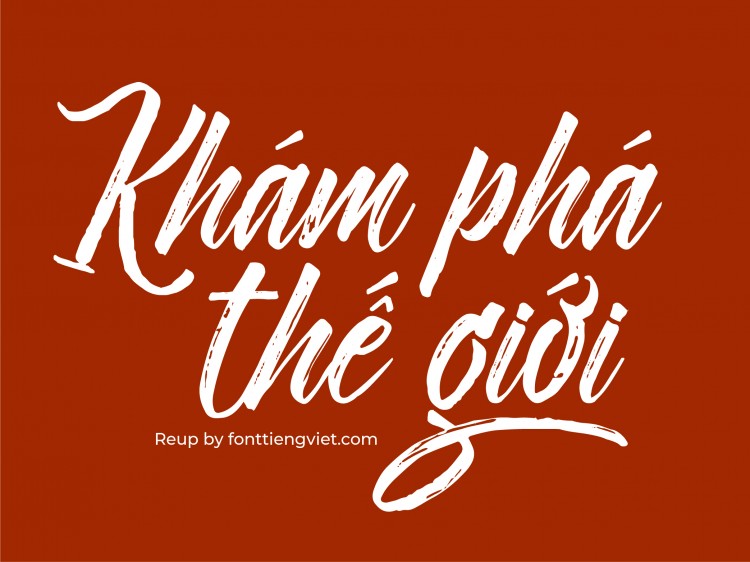
Font việt hóa FS Novitha Script
Tải Font việt hóa FS Novitha Script Miễn Phí Cho Thiết Kế Thư Pháp Hiện Đại
Giới thiệu về Font việt hóa FS Novitha Script
Trong thế giới đồ họa hiện đại, việc tìm kiếm một bộ Font Miễn Phí mang phong cách mềm mại nhưng vẫn giữ được sự chuyên nghiệp là điều rất quan trọng. Font việt hóa FS Novitha Script chính là giải pháp hoàn hảo cho các bạn học sinh và giáo viên khi muốn trang trí tài liệu học tập hoặc làm thiệp chúc mừng. Đây là kiểu chữ Script dạng viết tay đầy uyển chuyển, mang đậm nét nghệ thuật thư pháp đương đại. Khi được việt hóa chỉn chu, bộ font này loại bỏ hoàn toàn lỗi hiển thị dấu tiếng Việt, giúp người dùng tự do sáng tạo mà không gặp bất kỳ rào cản kỹ thuật nào.
Đặc điểm nổi bật của bộ font chữ nghệ thuật này
Phong cách thiết kế thanh lịch
Font việt hóa FS Novitha Script sở hữu những đường nét thanh mảnh, uốn lượn tự nhiên như nét bút lông trên giấy. Các ký tự được liên kết với nhau một cách tinh tế, tạo ra nhịp điệu thị giác rất cuốn hút. Điều này đặc biệt phù hợp cho các tiêu đề báo tường, trang trí bìa giáo án hay các dự án thiết kế đòi hỏi tính thẩm mỹ cao và sự gần gũi.
Khả năng ứng dụng linh hoạt
Dù là thiết kế trên Canva, Photoshop hay Word, bộ font này đều hoạt động mượt mà. Với đầy đủ các ký tự đặc biệt và dấu câu tiếng Việt, bạn có thể sử dụng nó để làm nổi bật các câu trích dẫn hay tạo ra những logo cá nhân độc đáo. Sự kết hợp giữa nét cổ điển và hiện đại giúp tác phẩm của bạn trở nên ấn tượng hơn trong mắt người xem.